1、精选手写书法字体
精选手写书法字体一共有三十款常见的书法字体,比方说方正大草简体、毛泽东字体、钟奇志莽行书、印品赤壁赋字体、金梅草行书体等等,每一款都非常有特色,如果大家喜欢,可以收藏一下。
2、手写字体打包
3、方正经黑手写简体
方正经黑手写简体也属于方正手写字体中的一款,支持中英文、阿拉伯数字等,字形圆润、十分醒目,线条自然、简洁,大家可以下载体验一下。
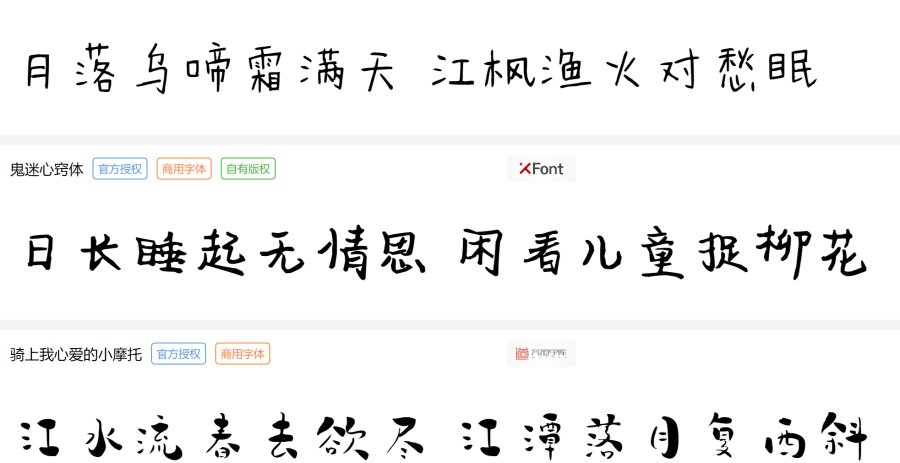
所谓的手写体字体,都是字体大师们手工书写出来的字体。很多朋友都对好看的手写字体十分感兴趣,在这里,印品字体小编专门为大家整理了手写字体下载大全,好看的手写字体大全有哪些,一起来看一下吧。